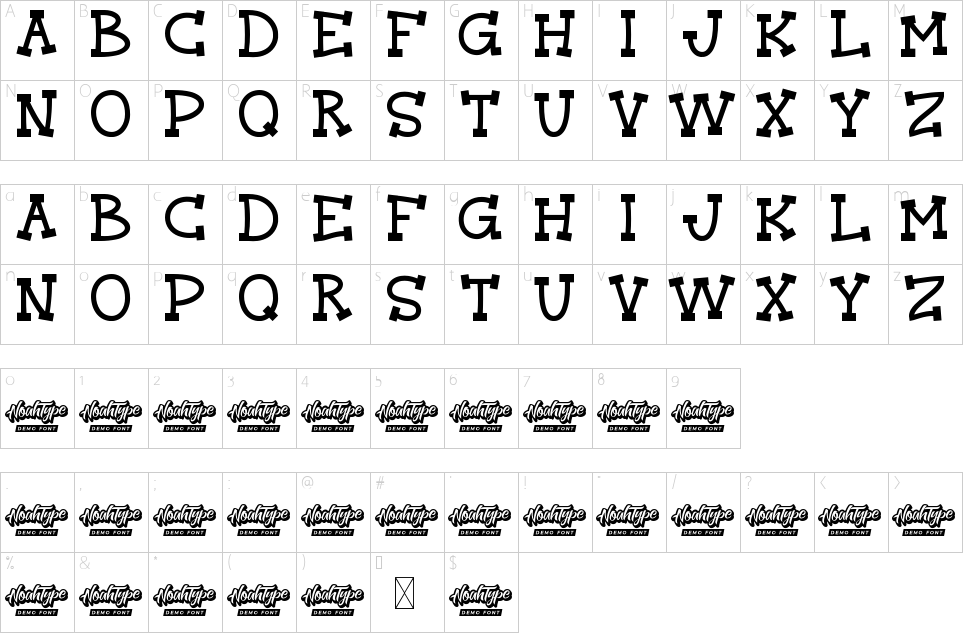
Descubra a beleza e a elegância da fonte Marvin Pablo, uma escolha perfeita para designers e amantes do design gráfico em busca de uma fonte de qualidade gratuita. Designada por NoahType, essa fonte está disponível para sistemas Windows e Mac, permitindo que você personalize seu design sem limitações. Marvin Pablo não apenas oferece uma variedade de caracteres únicos, mas também uma aparência arredondada e confortável, tornando-a uma escolha inteligente para qualquer projeto, desde a criação de logotipos até a desenvolvimento de aplicativos. Com uma baixa taxa de download de 2.444 vezes, isso demonstra a popularidade e qualidade dessa fonte. Instale Marvin Pablo hoje e adicione um toque de sofisticação e unicidade a seus projetos.